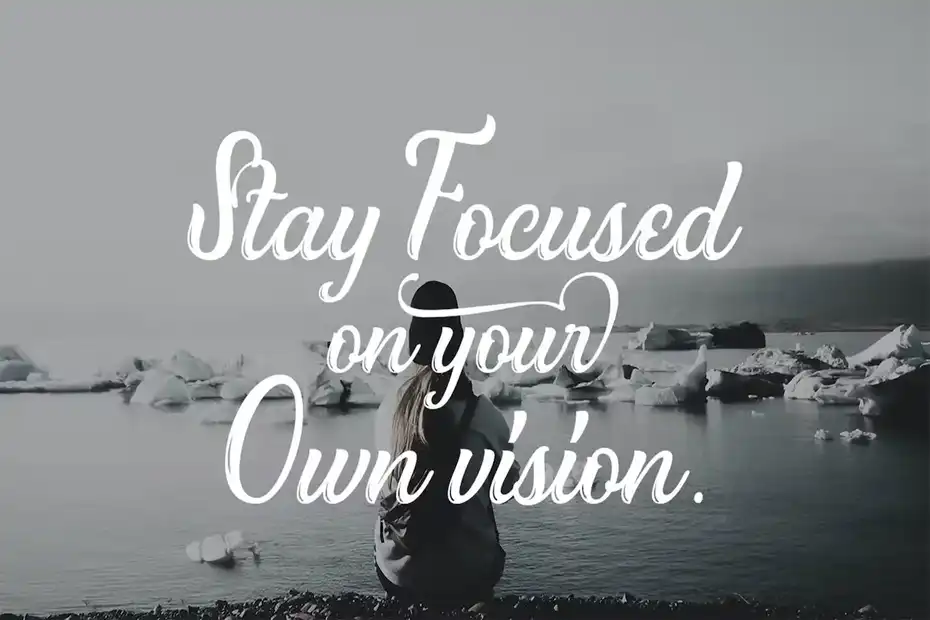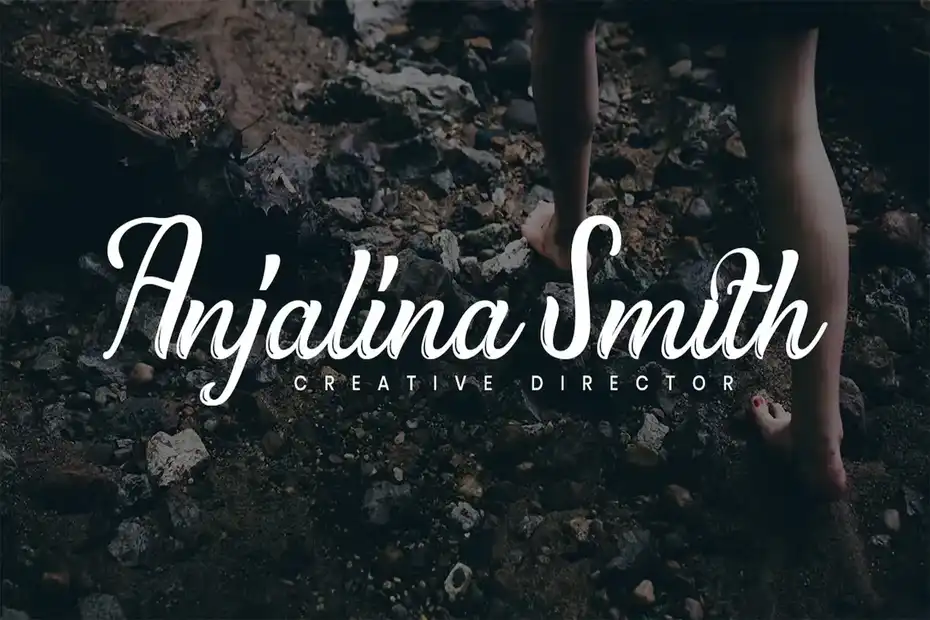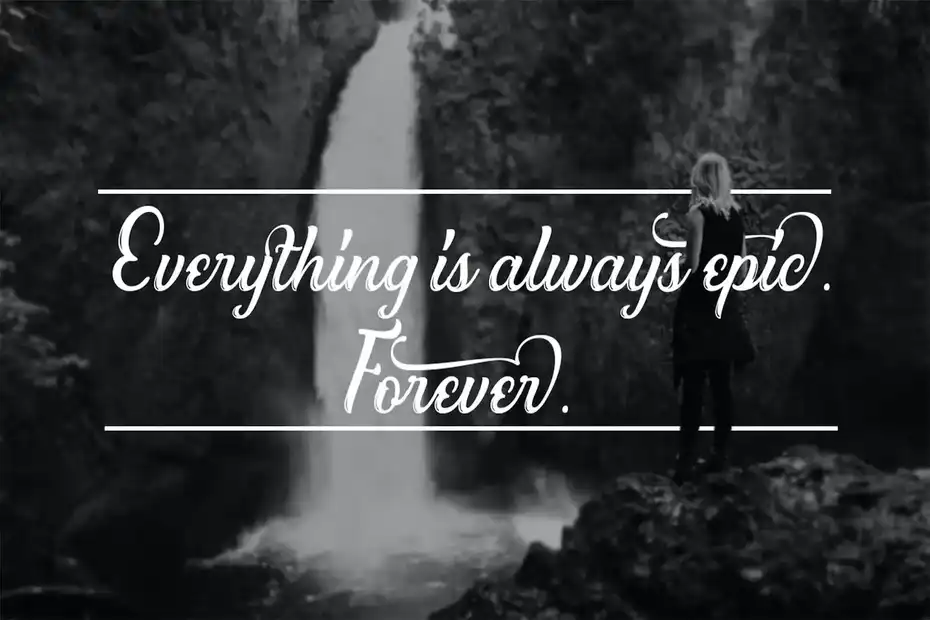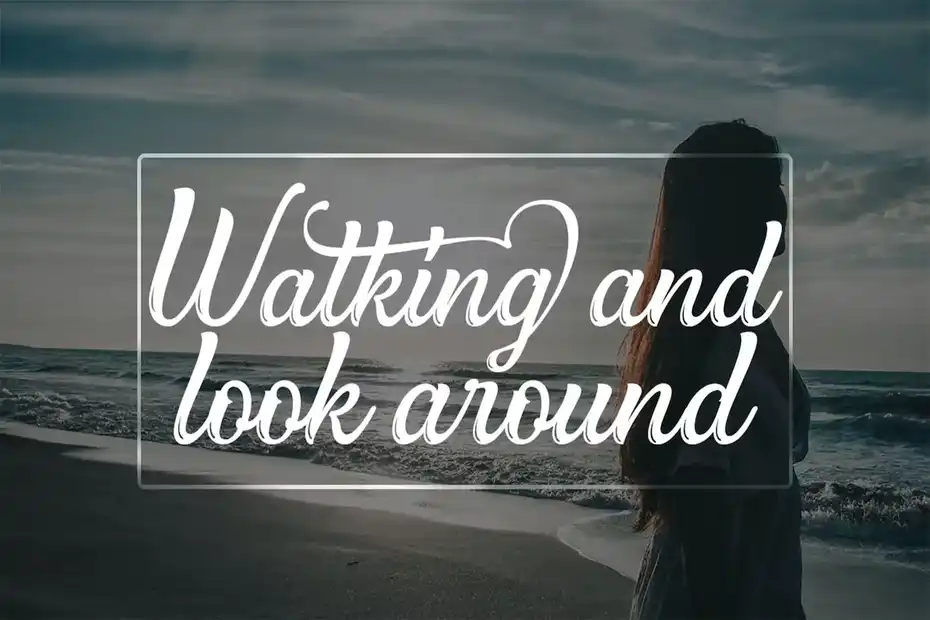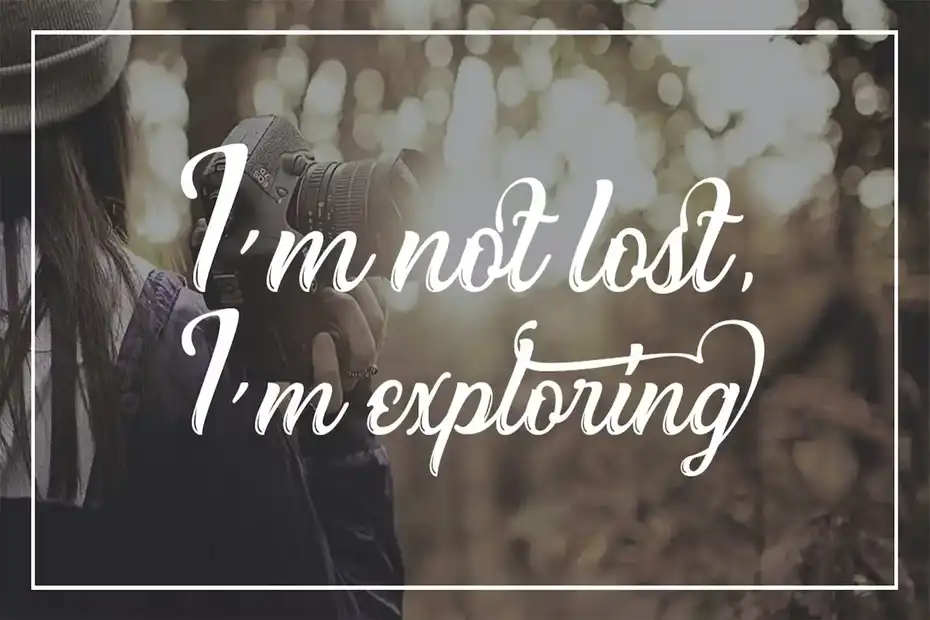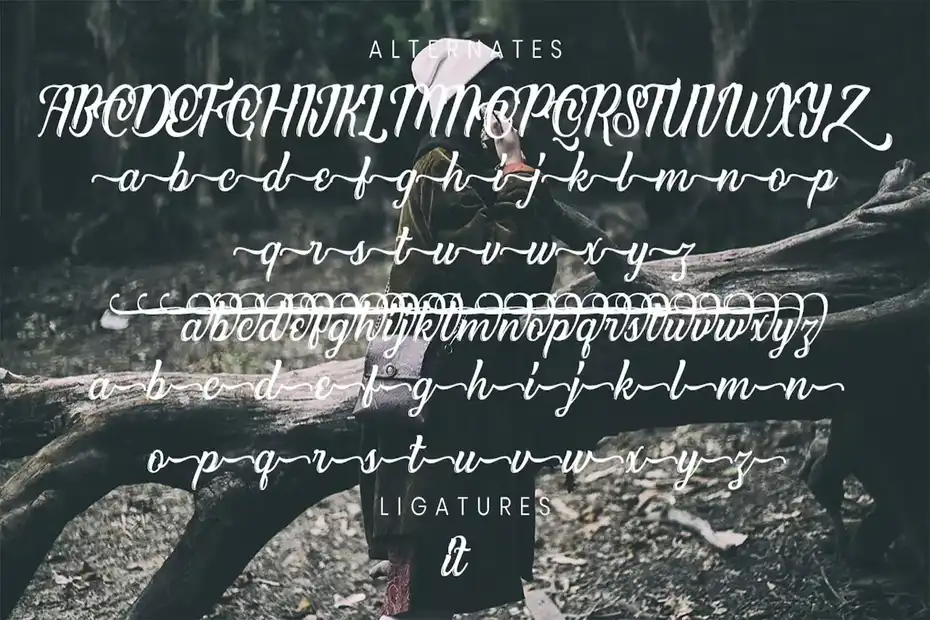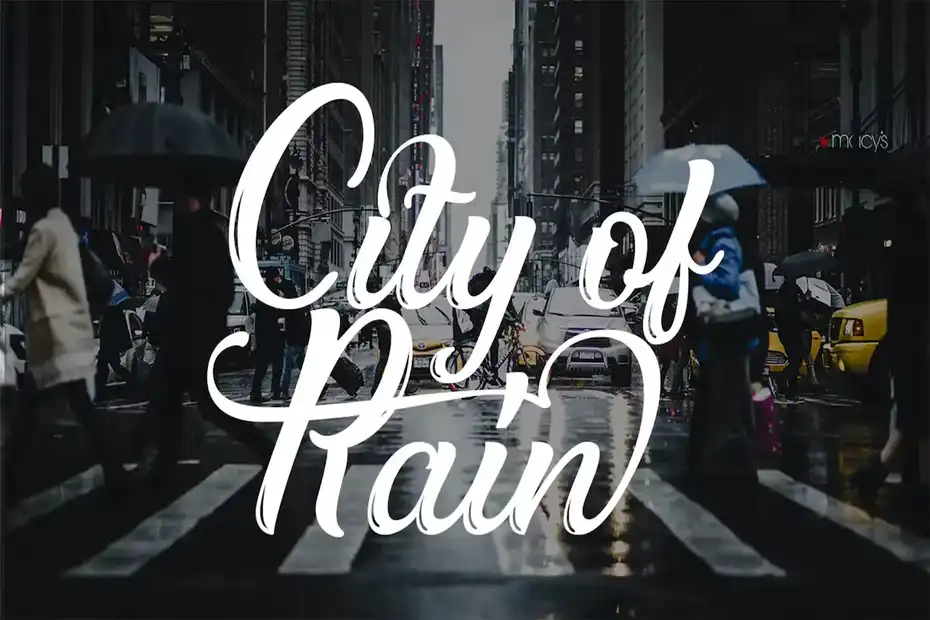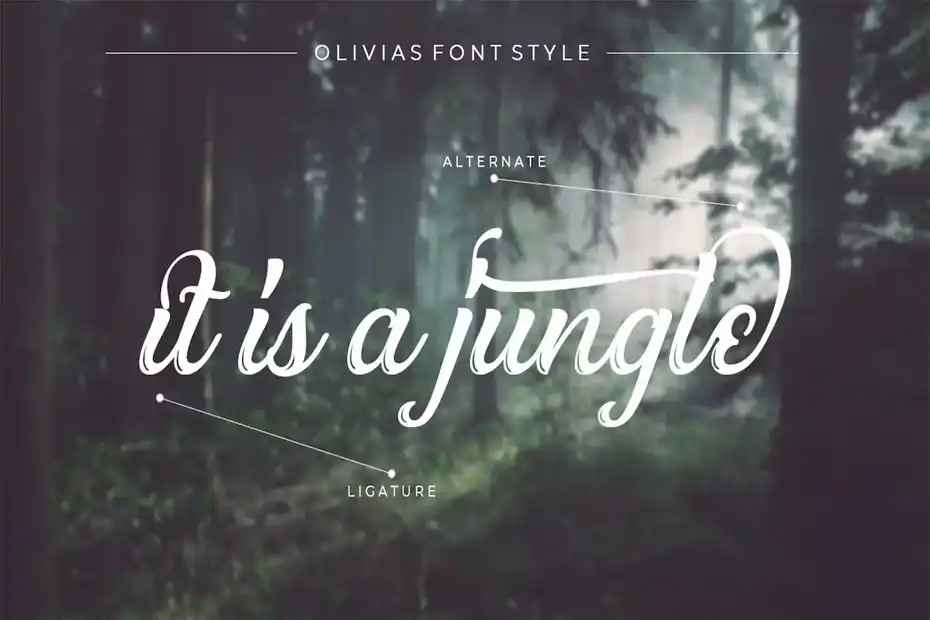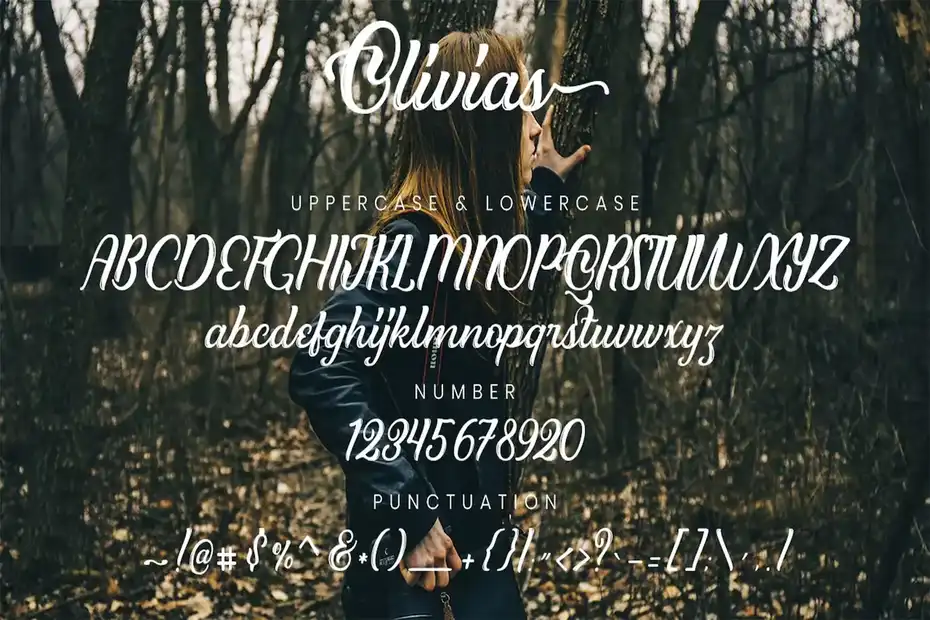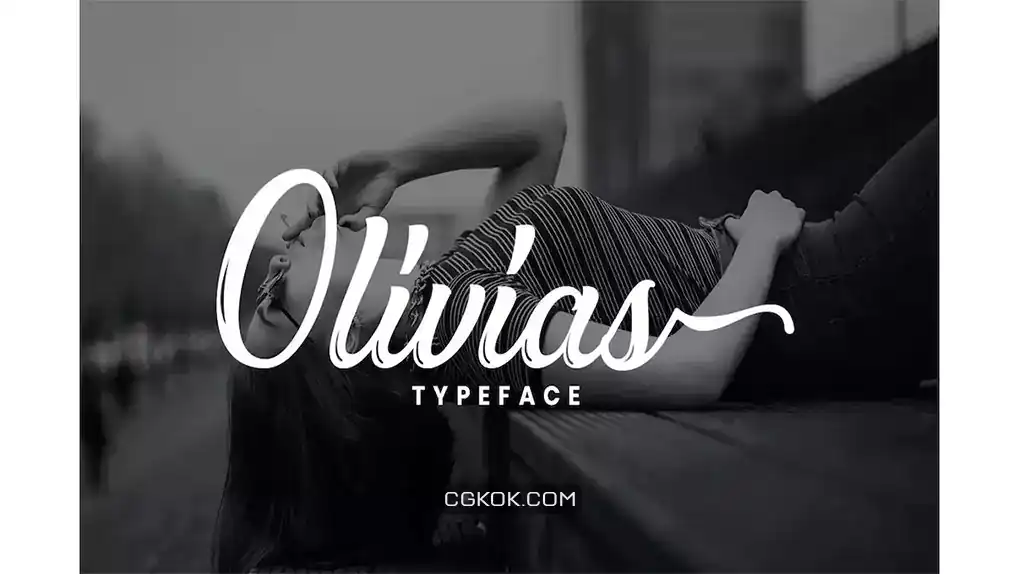
فونت انگلیسی Olivias Typeface : این فونت یک اسکریپت تایپ فیس به سبک خوشنویسی است که برای لوگو، پوستر، برندینگ، نقل قول، محصول، کالا، لیبل و غیره مناسب میباشد.